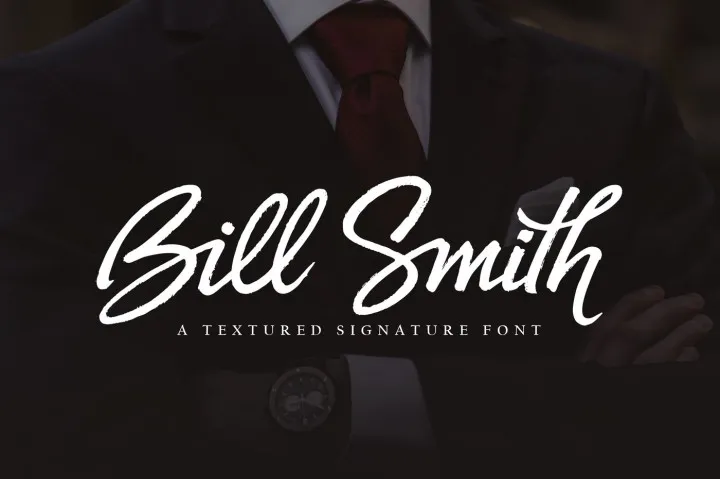
Bill Smith Script Font – Download Grátis
Se você é um entusiasta do tipo-fonte ou simplesmente busca a perfeição na simplicidade, você vai adorar conhecer o Bill Smith Font. Esta nova fonte assinatura foi criada pelo Subectype e tem um estilo texturizado único. Uma das características mais apreciadas é sua simplicidade, que faz dela uma opção ideal para muitos projetos de design gráfico. Seja para fotografias profissionais, assinaturas de alta qualidade, criações de marca ou qualquer outro projeto em que você precise de um tipo-fonte forte e elegante, o Bill Smith tem seu lugar. Com certeza, essa font será uma ótima adição a sua coleção de recursos gráficos.